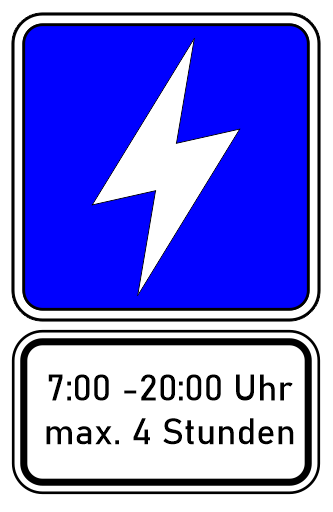
[Mitglied dean…] Geschrieben März 16, 2021 Teilen Geschrieben März 16, 2021 Frage würde das gehen an alle? warum worum gehts? Berlin hat auch deppen. die brauchen 3 schilder um "grüne Parkplätze zu lesen. ist ein scribble noch nicht endfassung. https://ibb.co/vsWr3mF schade dass die RAL-Farben nicht den Namen Straßengrün sondern Verkehrsgrün nennen. ok RAL ist schon älter als RAL+F aber da könnte man so schön das grosse ß platzieren mit der schönen schrift Wayfinder pro @Ralf Herrmann schau mal hier https://ibb.co/n3TnM2p ist das gewollt? Hermann und Gerrman---German Herrmann? Link zu diesem Kommentar
[Mitglied 1728…] Geschrieben März 16, 2021 Teilen Geschrieben März 16, 2021 Viel verstanden habe ich von deinem kryptischen Text nicht … falls deine Frage ist, ob ein Verkehrszeichen 314 auch grün sein darf: Nein, darf es nicht, es muss blau sein. Infos zur Beschilderung findest du hier: http://www.vzkat.de/2018/Elektrofahrzeuge/Elektrofahrzeuge-Ladestationen.htm Was sind denn "grüne Parkplätze"? Link zu diesem Kommentar
[Mitglied dean…] Geschrieben März 16, 2021 Themen-Ersteller Teilen Geschrieben März 16, 2021 Ein wenig habe ich mich mit verkehrsteichen ooops Verkehrszeichen soll es heissen befasst es gibt NORMEN etc. das problem kurz geschildert e-autofahrer tankt an seiner e-tanksäule und der wird zu geparkt oder ein anderer steht drauf. immer noch unverständlich? ich finde gerade den beitrag nicht. sonst hätte ich ihn dir natürlich verlingt - Ralf wird da vermutlich mehr sagen können. es geht um die Lesbarkeit. ja es gibt die netten farben rot-gelb grün blau schwarz weiss. ich kann den mann verstehen der eine petition starten will dass Berlin 3 schilder für eine E-Säule braucht.und nicht einmal die Polizei eine Antwort hat. Dsas ist peinlich für Berlin, das sage ich als Berliner. klar wir wollen alle geld verdienen aber unter dem strich zahlen wir all wieder. immer noch kryptisch? Gruss Dean, danke und bleib/t gesund. mobil gesendet. Link zu diesem Kommentar
[Mitglied dean…] Geschrieben März 16, 2021 Themen-Ersteller Teilen Geschrieben März 16, 2021 vor 8 Minuten schrieb deaneau: Ein wenig habe ich mich mit verkehrsteichen ooops Verkehrszeichen soll es heissen befasst es gibt NORMEN etc. das problem kurz geschildert e-autofahrer tankt an seiner e-tanksäule und der wird zu geparkt oder ein anderer steht drauf. immer noch unverständlich? ich finde gerade den beitrag nicht. sonst hätte ich ihn dir natürlich verlingt - Ralf wird da vermutlich mehr sagen können. es geht um die Lesbarkeit. ja es gibt die netten farben rot-gelb grün blau schwarz weiss. ich kann den mann verstehen der eine petition starten will dass Berlin 3 schilder für eine E-Säule braucht.und nicht einmal die Polizei eine Antwort hat. Dsas ist peinlich für Berlin, das sage ich als Berliner. klar wir wollen alle geld verdienen aber unter dem strich zahlen wir all wieder. immer noch kryptisch? Gruss Dean, danke und bleib/t gesund. was hast denn verstanden ###mobil gesendet### Link zu diesem Kommentar
[Mitglied 1728…] Geschrieben März 16, 2021 Teilen Geschrieben März 16, 2021 vor 7 Minuten schrieb deaneau: immer noch unverständlich? immer noch kryptisch? Ja, immer noch. Geht es dir darum, ein neues Verkehrszeichen "Parkplatz für E-Fahrzeuge" zu erfinden? Die gültigen Zeichen nebst Kombinationen mit Zusatzzeichen (es gibt ja hunderte Möglichkeiten mehr als in deinem einen Schild dargestellt) habe ich dir ja verlinkt. Link zu diesem Kommentar
[Mitglied dean…] Geschrieben März 16, 2021 Themen-Ersteller Teilen Geschrieben März 16, 2021 Lieber guter Kollege Bertel... es gibt kreative Köpfe genug die jeden Tag etwas neues erfinden, aber wo nach sieht es denn aus? Betrachte das Bild eine Weile und lasse es wirken. ich sehe ein Bild und du? Gruss Dean Link zu diesem Kommentar
[Mitglied dean…] Geschrieben März 16, 2021 Themen-Ersteller Teilen Geschrieben März 16, 2021 @bertel kein ding blau ist die bessere wahl weil ein grüner hintergrund und grün nicht so recht passt. also grün auf grün und weiss- das kann auch gern blau sein nach DIN DORM oops NORM. ok was siehst du Bertel mal von der beschriftung RAL abgesehen die gehört natürlich nicht dazu. die hatte ich nur reinesetzt damit die frage die immer kommt welche farbe ist es denn bla bla https://de.wikipedia.org/wiki/Vergleich_europäischer_Verkehrszeichen DINISO... jetzt fehlt nur noch WA oder VA am ende und wir sind hier angelangt Denisova-Mensch Der Dinisova-Mensch ist dann der, der alles ganz nach DIN und ISO braucht. Link zu diesem Kommentar
[Mitglied Andr…] Geschrieben März 16, 2021 Teilen Geschrieben März 16, 2021 Nein, das ist ein sehr hilfsbereiter Kollege, der sich nur fragt, wobei du jetzt Hilfe brauchst. 1 Link zu diesem Kommentar
[Mitglied Muec…] Geschrieben März 16, 2021 Teilen Geschrieben März 16, 2021 ... oder uns vom Frühstück was abgeben, vielleicht verstehen wir die Frage dann besser ... 😁 1 2 Link zu diesem Kommentar
[Mitglied Phoi…] Geschrieben März 16, 2021 Teilen Geschrieben März 16, 2021 vor 5 Stunden schrieb deaneau: https://ibb.co/vsWr3mF Sollte ich Dich richtig vestanden haben, fragst Du hier nach unserer Meinung zu. Also ich sehe ein P für Parkplatz, dass zu einem Stecker aufgebohrt wurde mit seitlicher Stromzuführung. Grüne Verkehrsschilder kenne ich so nicht, grün kommt hier nur bei Bushaltestellen auf gelben Grund vor oder um irgendwas Interessantes zu beschriften oder anzuzeiten wie "Flussname" oder "Da geht es zum Hünengrab". Und es gibt noch Europastraßen (glaub ich zumindest, hab keinen Führerschein)). Was aber nicht geht, ist die Parkbegrenzung auf vier Stunden, da ich als Stundenabkürzung das h nur kleingeschrieben kenne und es auch so als Einheitenzeigen SI-konform ist. 1 Link zu diesem Kommentar
[Mitglied 510e…] Geschrieben März 16, 2021 Teilen Geschrieben März 16, 2021 Obwohl vieles dagegen spricht hier zu antworten (von den wirren Posts über die schreckliche Werbung/Clickbait bis zur eigenartigen Darstellung des Entwurfs), sondere ich hier trotzdem mal meine Meinung ab: Das P sieht sehr nach einem verkorksten Währungszeichen aus Währungszeichen zeichnen sich ja vermehrt durch zwei (horizontale) Striche aus – vielleicht eine gehypte Kryptowährung, die man braucht um die Parkgebühr bezahlen zu können Wofür ist das ›noch nicht die Endfassung‹? Ist das reine Spielerei? Gibt es einen Auftrag oder einen Wettbewerb? Was ist die Anforderung? Ansonsten als Tipp: Niemals die Farbangaben etc. in den Entwurf reinschreiben, die Farbe sieht man doch und Fragen in ganzen und verständlichen Sätzen stellen ... Link zu diesem Kommentar
[Mitglied catf…] Geschrieben März 16, 2021 Teilen Geschrieben März 16, 2021 oder als Batterie-Ladesymbol: https://www.google.com/search?q=Batterie+lade+symbol&client=firefox-b-d&sxsrf=ALeKk03R1Xq_WgKknj4BssY-oZXZkT-nJw:1615914563840&source=lnms&tbm=isch&biw=1024&bih=549#imgrc=jMoyx88FLedd7M Link zu diesem Kommentar